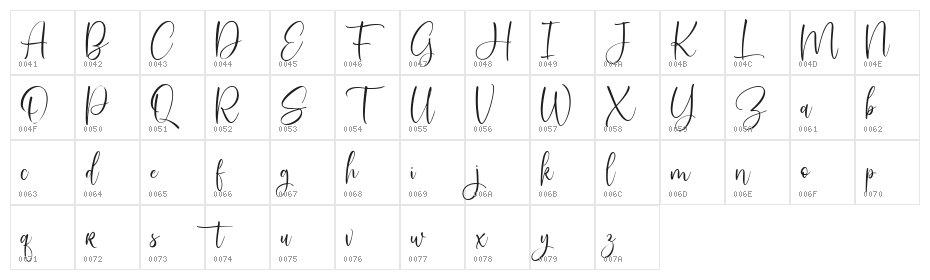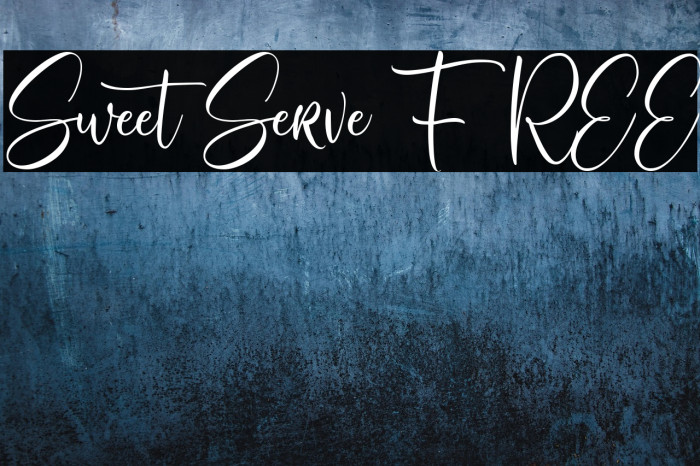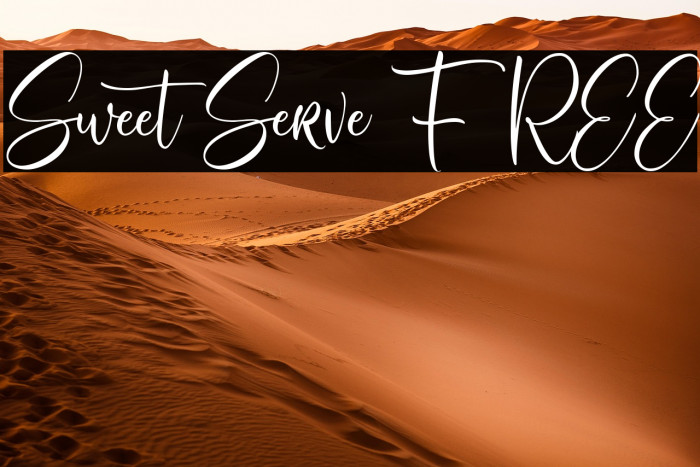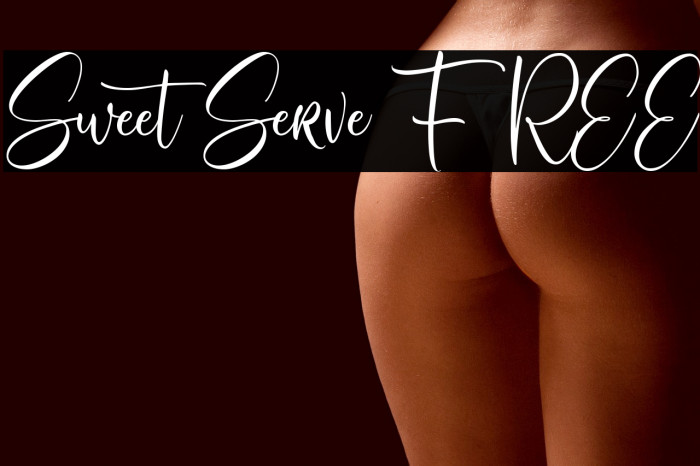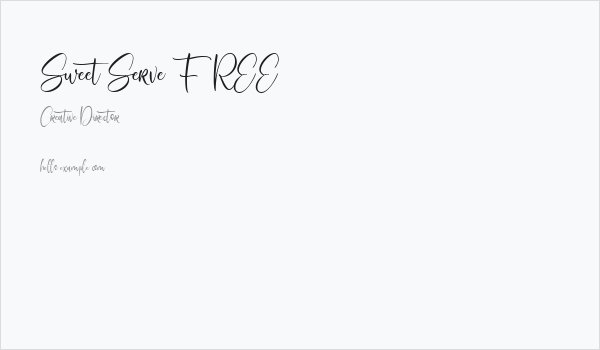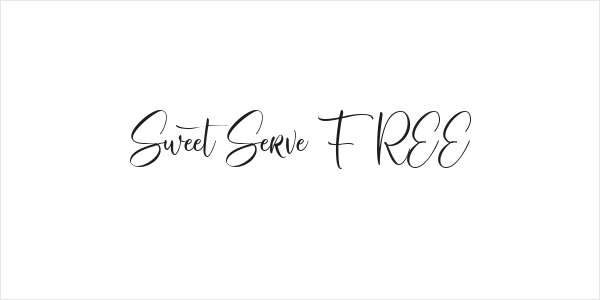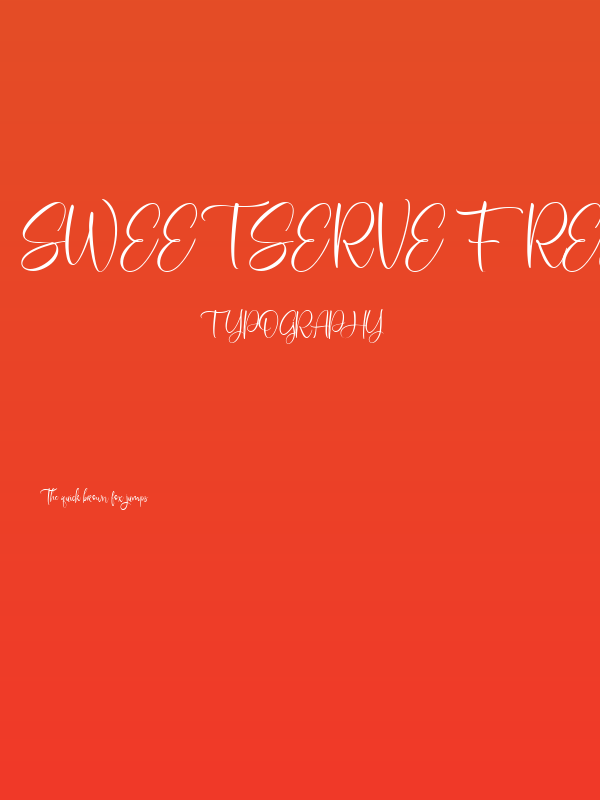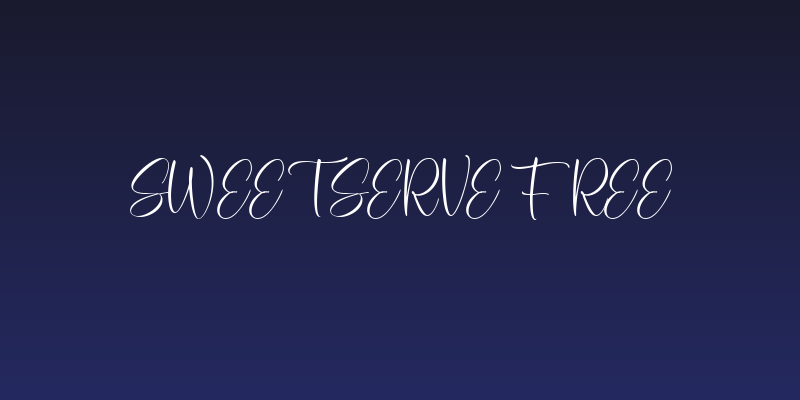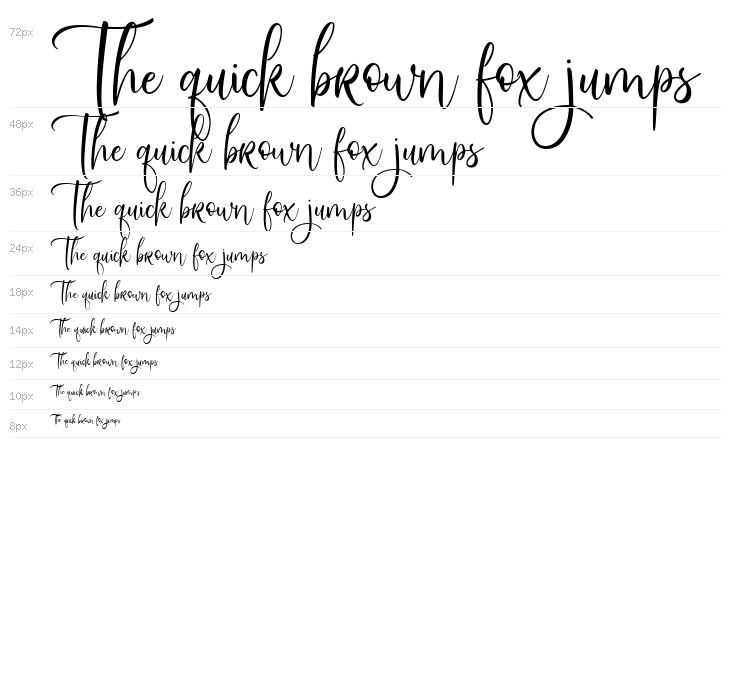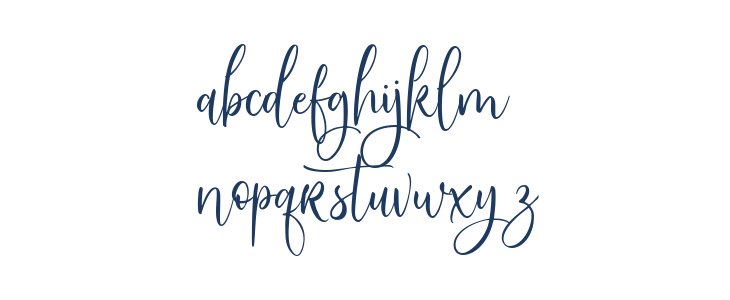
SweetServe FREE Font
| Общий стиль | Modern, Elegant |
| Область применения | Logos, Invitations, Branding |
| Рекомендуемые проекты | Ideal for wedding invitations, greeting cards, branding, and logo design where elegance and a personal touch are desired. |